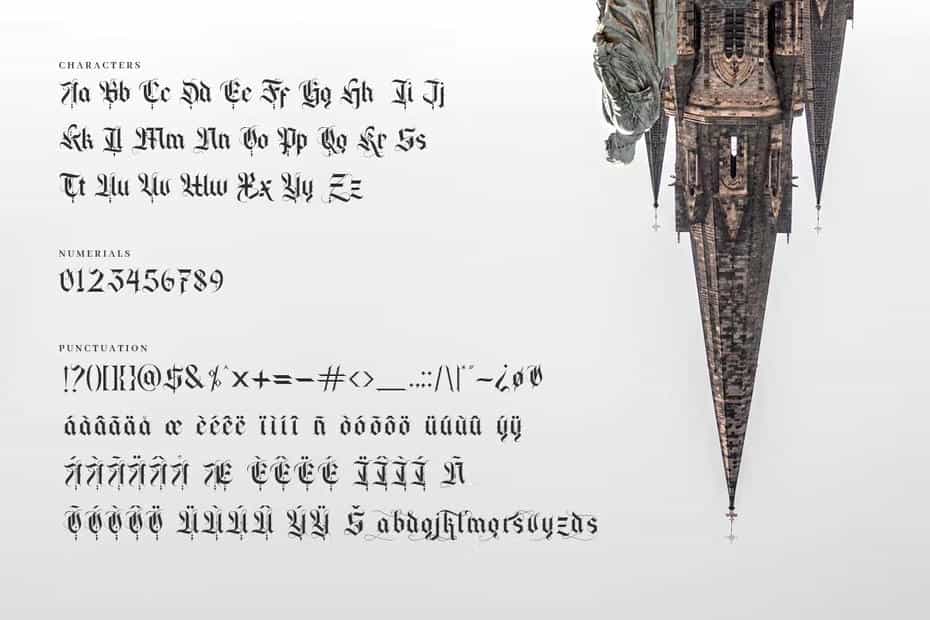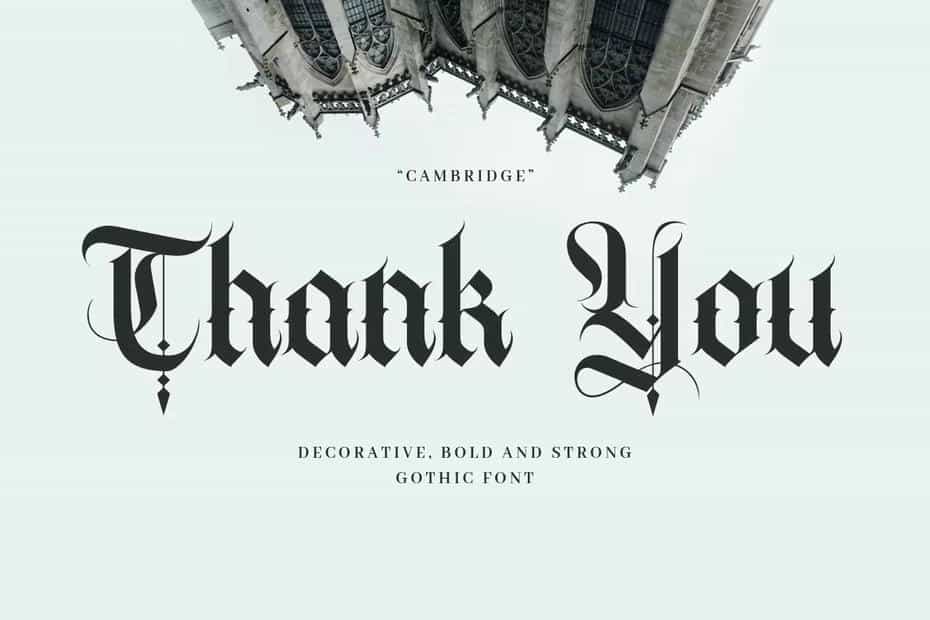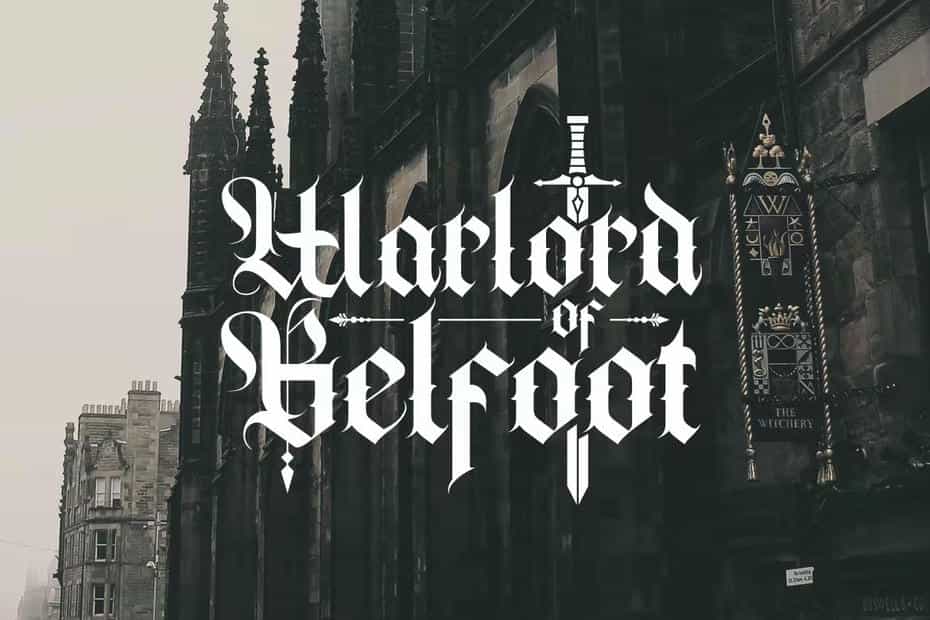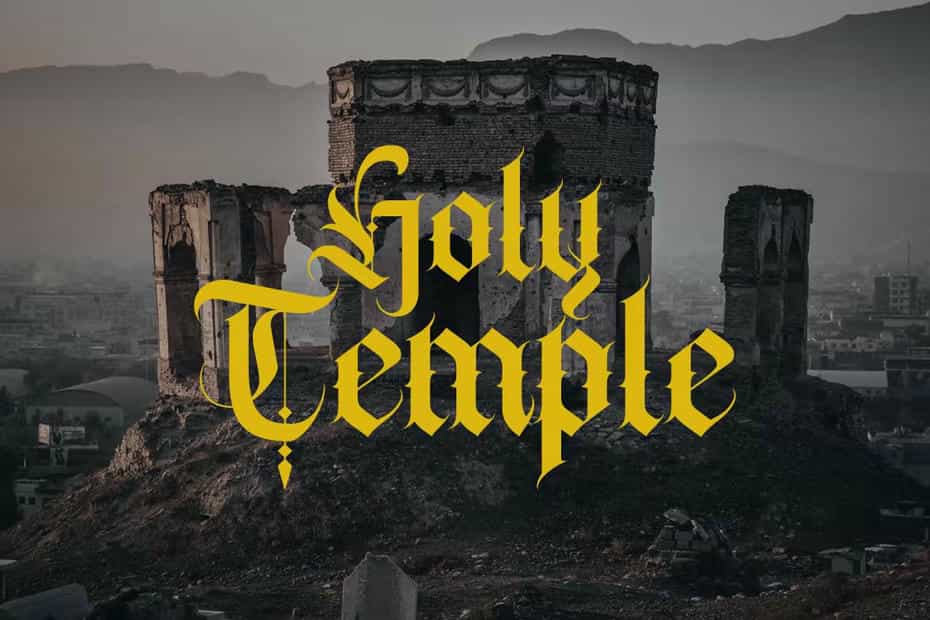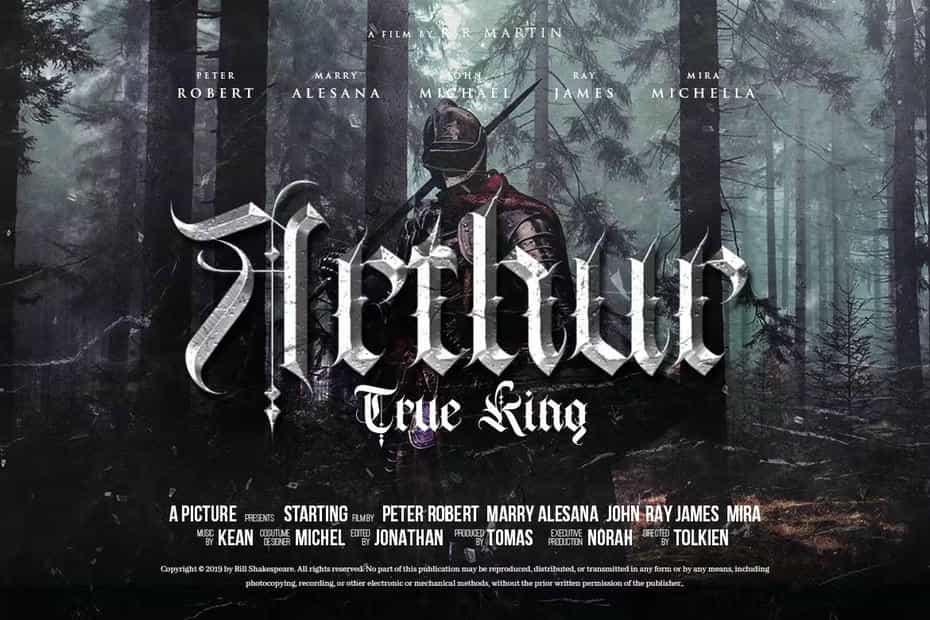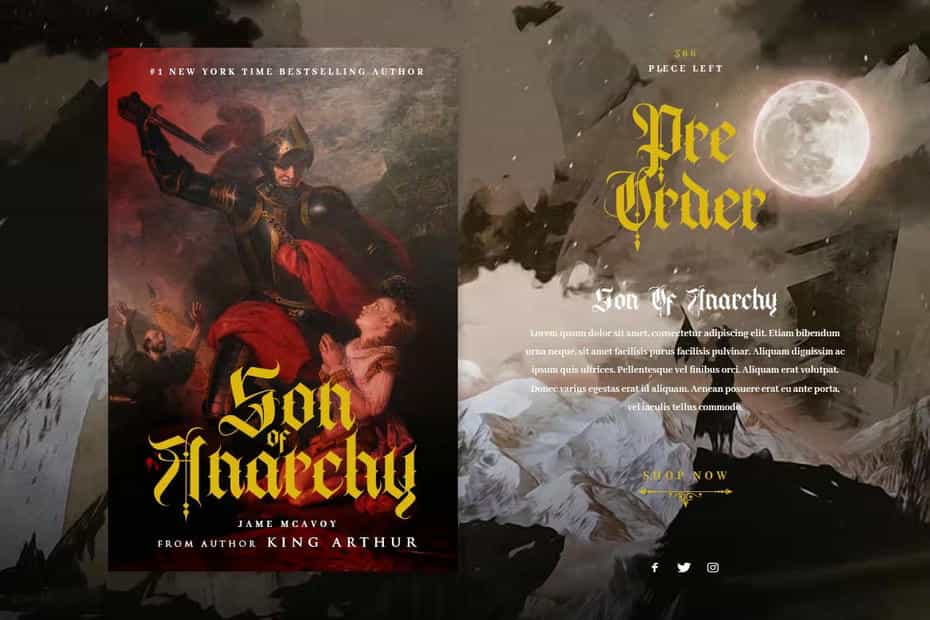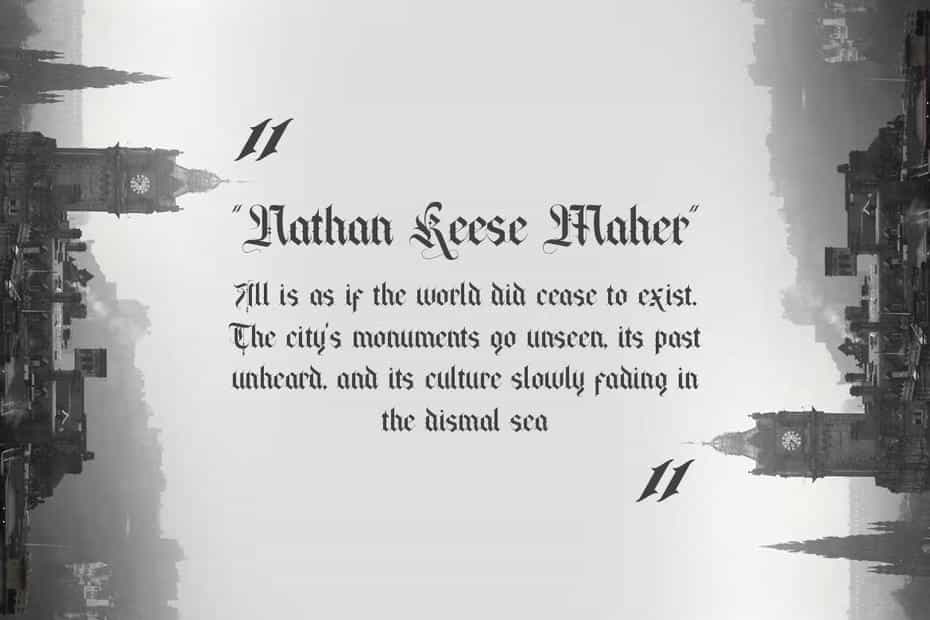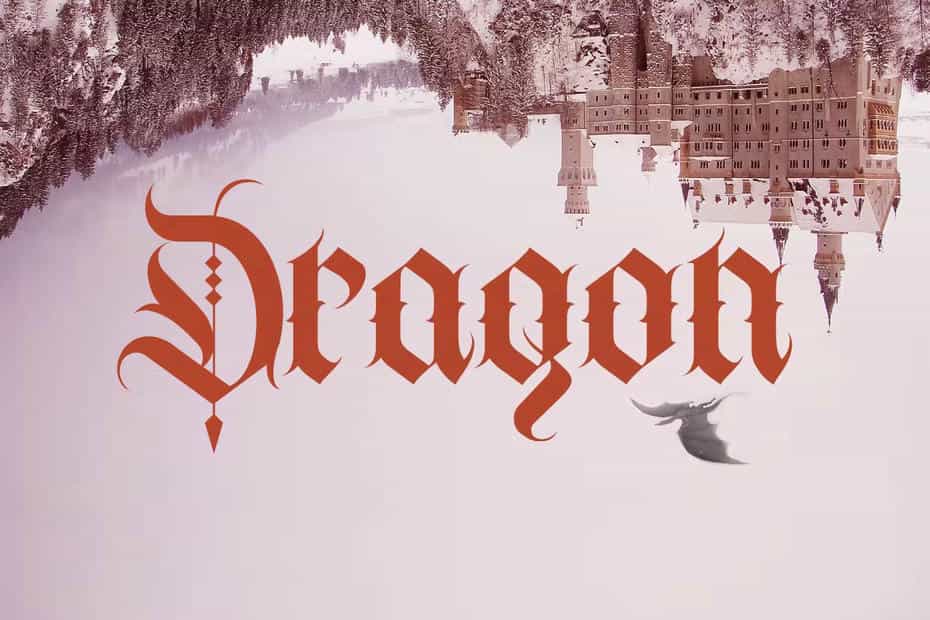
فونت انگلیسی Cambridge : این مجموعه شامل یک فونت تزئینی به سبک قرون وسطایی است که برای کتاب، لوگو، چاپ، بازی، ایونت، موسیقی، دعوتنامه و … مناسب می باشد. می توانید از دسته بندی فونت انگلیسی کلاسیک در سایت سیجی کوک، فونت های کلاسیک انگلیسی مشابه را مشاهده و دانلود کنید.
- سبک: Serif
- فضا بین حروف: معمولی
- اندازه بهینه: بزرگ (نمایش / پوستر)